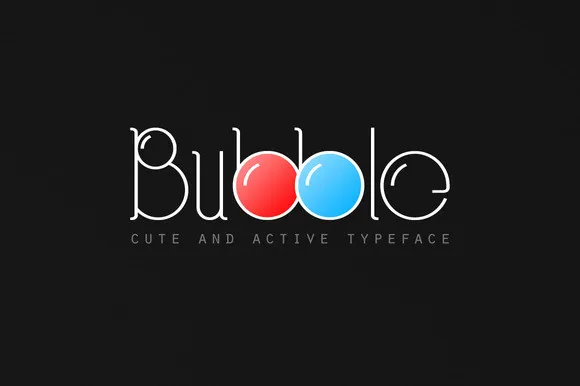
Bubble Typeface – Fonte Grátis
Bubble Typeface
Esta é uma fonte tipo ‘Bubble Typeface’, criada pelo designer Hamilton, que transmite alegria e encanto com sua coruja simétrica e elegante design. Perfeita para uso em design infantil ou criações inspiradas em crianças, esta fonte contém aproximadamente 200 caracteres. Acreditamos que você irá adorar essa fonte jovial e divertida. Ideal para tornar seus designs mais vivos e alegres, seja para rascunhos de atividades escolares ou criações infantis em geral. Estamos ansiosos para vê-la no seu próximo projeto!